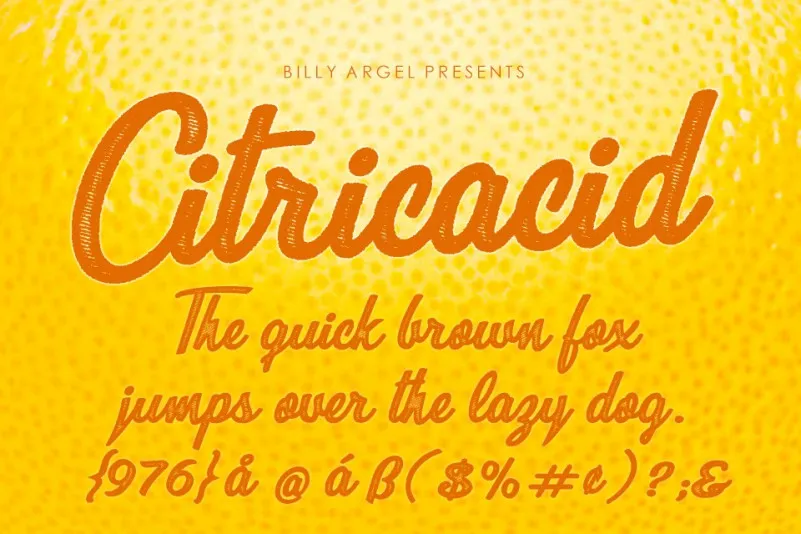
Citricacid Font
A Citricacid Font é uma criação vinda do design dos anos 70, que se tornou a representação visual perfeita para qualquer projeto moderno e vibrante. Inspirada no humor quente, nos movimentos boogaloo da era de ouro dos anos 70, além de seu estilo clássico porém não sério, essa fonte é fácil de lembrar e torna-se a cara de qualquer design. É uma escolha perfeita para designers que buscam algo diferente, único e extremamente acessível. A Citricacid Font se destaca na categoria de script fonts da 99designs, oferecendo um estilo divertido e irreverente, com um toque moderno que complementa qualquer design gráfico em desenvolvimento.